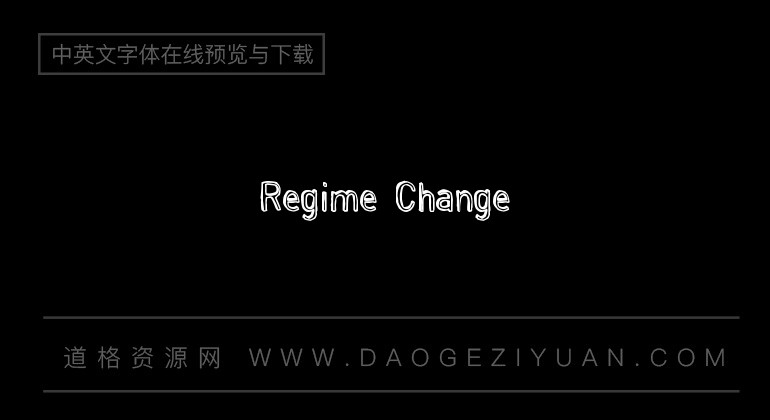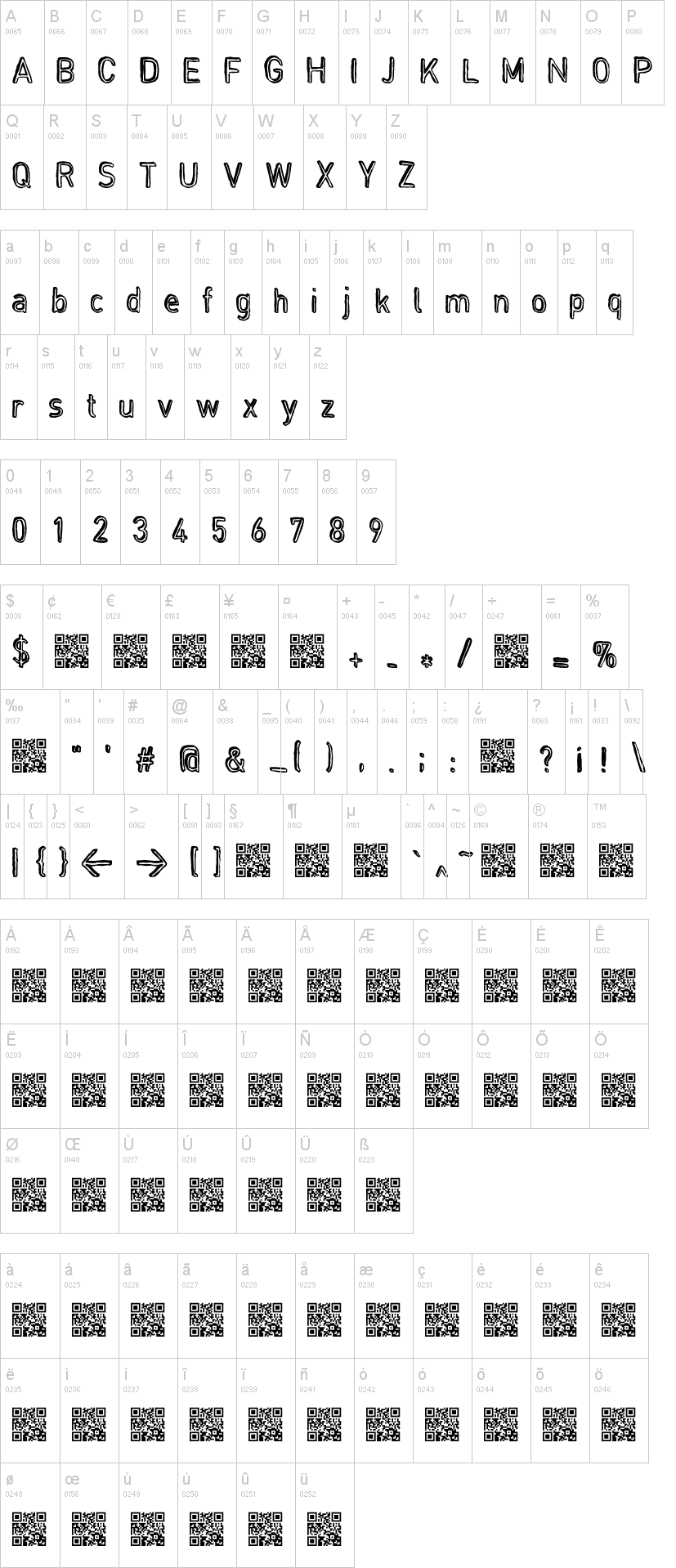
Regime Change
Regime Change 是一款字体,由设计师Rian Hughes设计,它是一款有趣的复古字体,具有独特的古典风格。它有一个细节丰富的外观,可以让文字看起来更有趣。它可以用于多种类型的设计,从海报到书籍,甚至是游戏设计,都能发挥出它的特色。它的特点是,它具有强烈的古典风格,但又不失现代感,能够为设计带来更多的灵活性和可能性。
Regime Change是一款非常不错的手写艺术字体,具有很好的视觉感,适合于文化类的宣传设计、商业类品牌的广告和产品包装设计以及个性化文字排版等较多场景。
Regime Change字符映射图